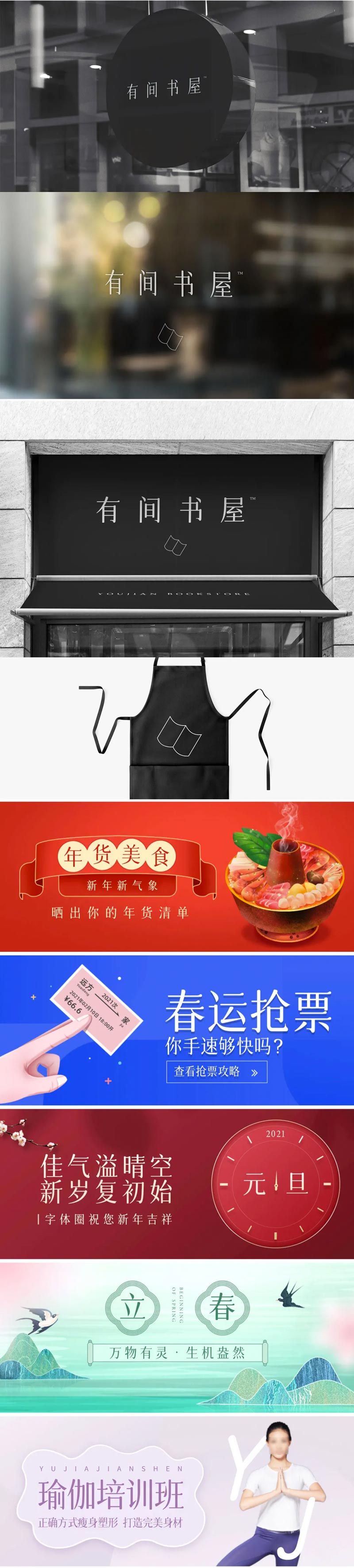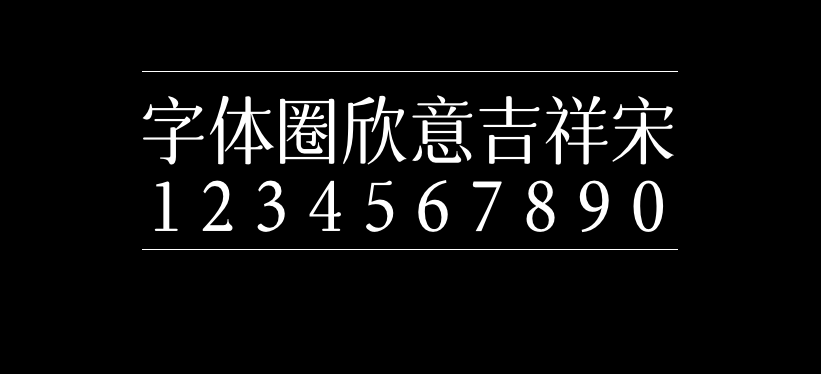
字体圈欣意吉祥宋
字体圈欣意吉祥宋是字体圈推出的第3款免费商用字体,这套字涵盖国家GB2312编码标准的6763个中文字符,52个英文字符,10个阿拉伯数字,若干个标点符号,按需添加若干生僻字,共7000余字符。这是一套宋体风格的标题字,风格整体偏圆润古风,目前市场上免费商用的宋体字,除了思源宋体,好像就是思源宋体的修改版,没有专门设计风格的宋体字。
据作者邹乐伟介绍,字体命名原本打算跟风格相同,欲名为“润宋体”,但没有什么特殊意义,毕竟免费字体可遇不可求,2020年确实是困难的一年,从年头到年尾非常艰难的度过,后来决定今天发布后,想到两个词“吉祥”与“平安”,纠结了好一会,最终定为“吉祥宋”,全名:字体圈欣意吉祥宋,很优雅的一个名字,祝愿今后每一年都能吉祥如意平安顺遂!